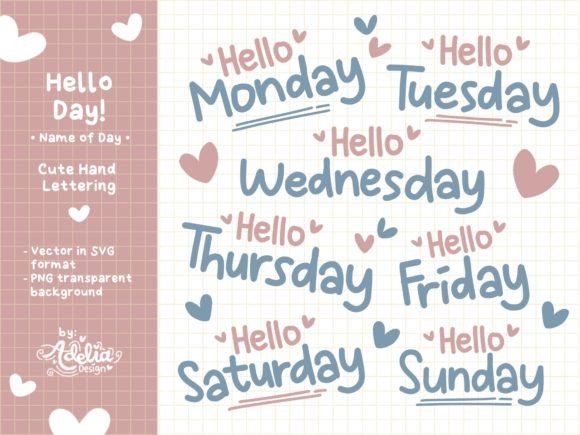
Hello Name of the Day
適切なデザイン要素を見つけるのは難しい場合がありますが、Hello Name of the Dayは作品を即座に引き立てる優れたコレクションを提供します。
POD(オンデマンド印刷)製品、結婚式の招待状、またはソーシャルメディアのグラフィックを作成している場合でも、Hello Name of the Dayは理想的です。